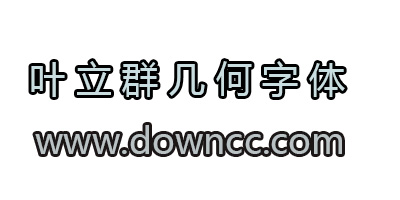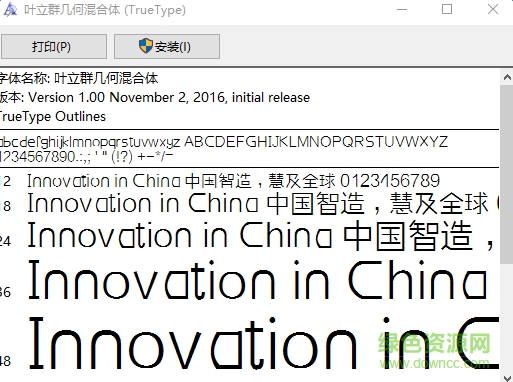
葉立群幾何混合體是葉立群字庫(kù)中的一款很實(shí)用的黑體字體,寫(xiě)出來(lái)的字粗細(xì)均勻,而且很耐看,適合書(shū)本印刷、藝術(shù)設(shè)計(jì)等方面,大家如果需要這款字體的話可以來(lái)綠色資源網(wǎng)下載。
葉立群幾何體 不僅僅是一款字體
葉立群幾何混合體是一款很有特色的字體,大氣美觀,大家快來(lái)綠色資源網(wǎng)下載使用吧。